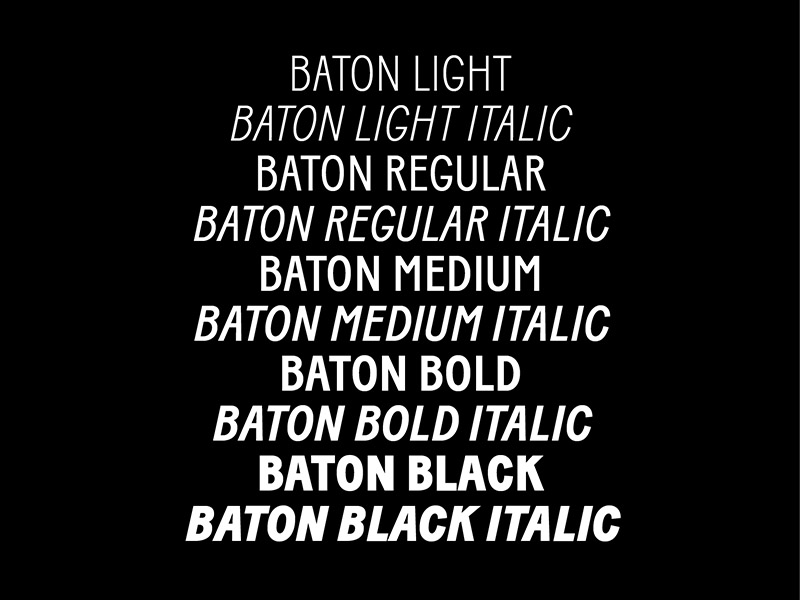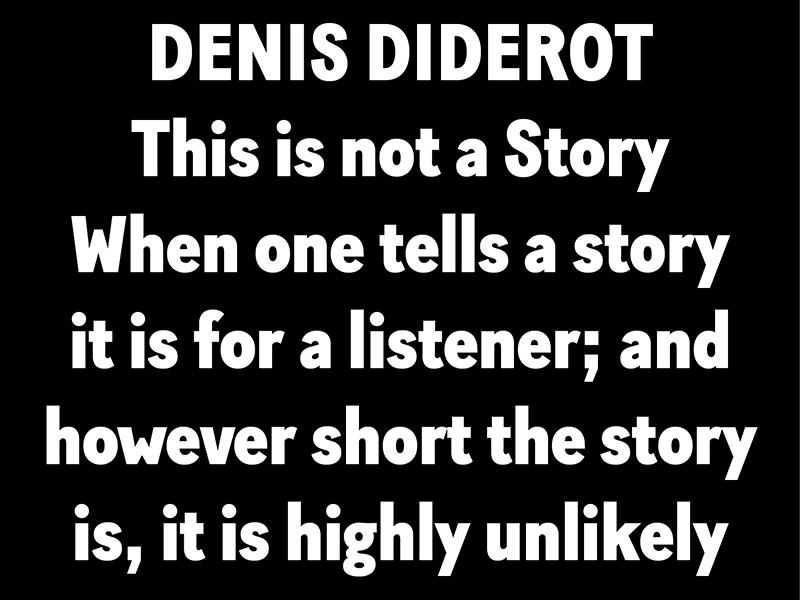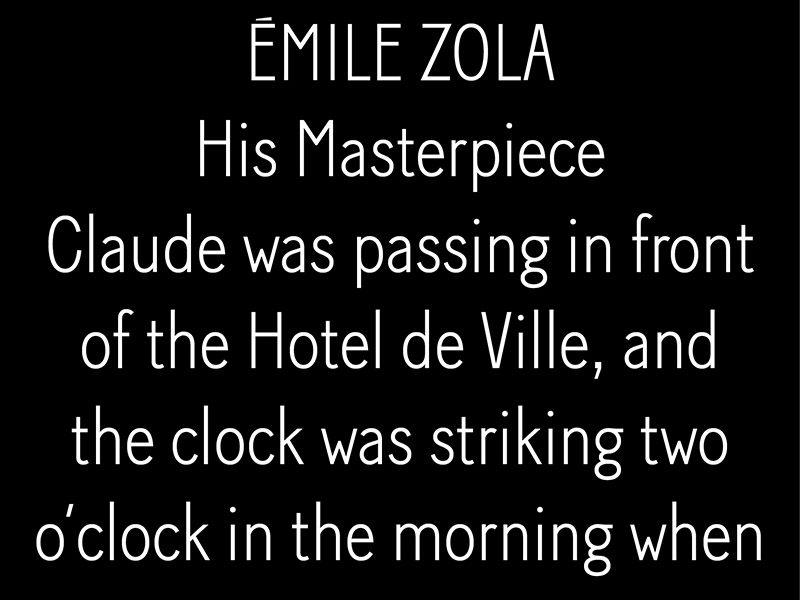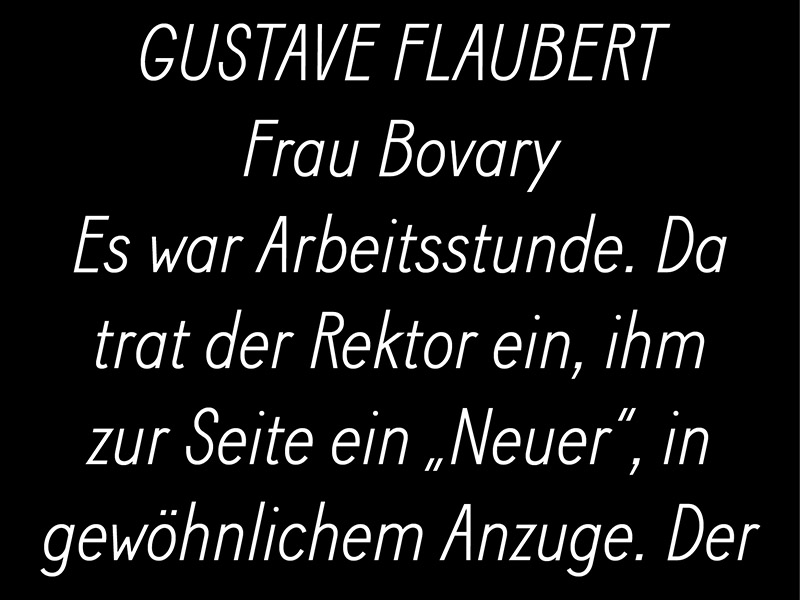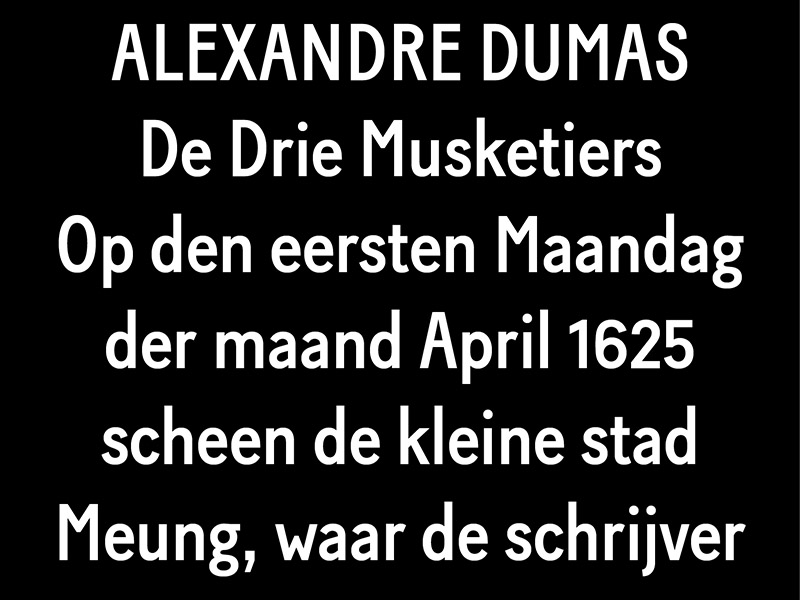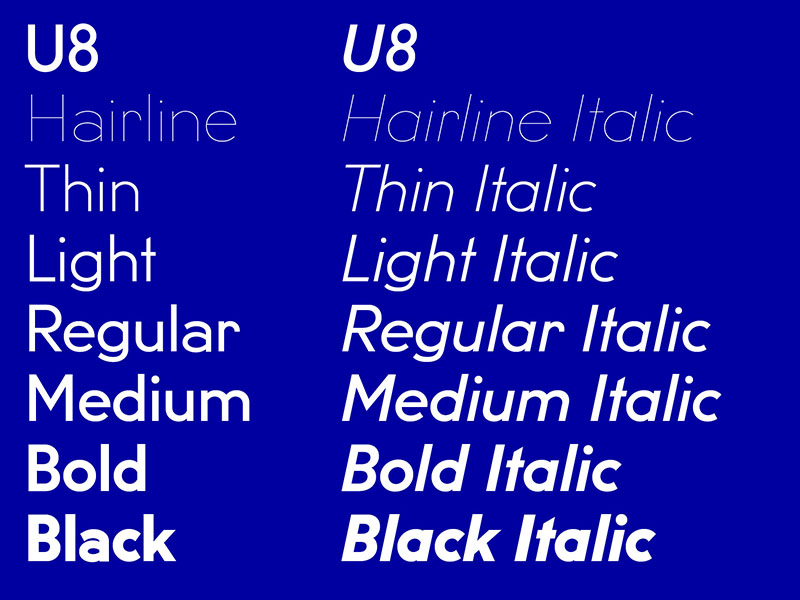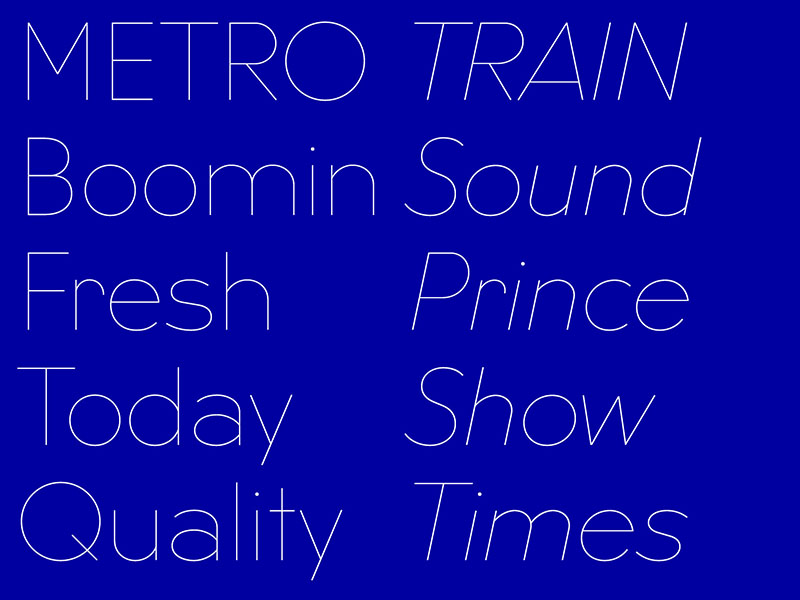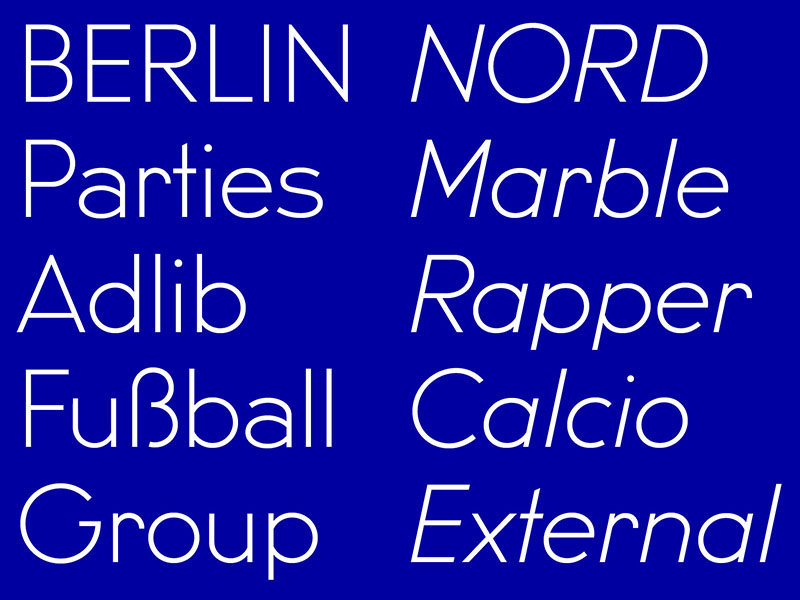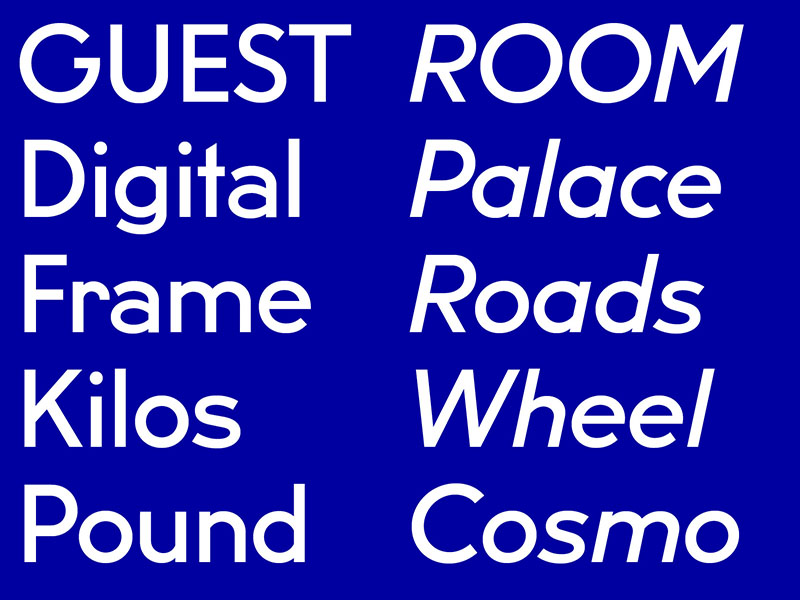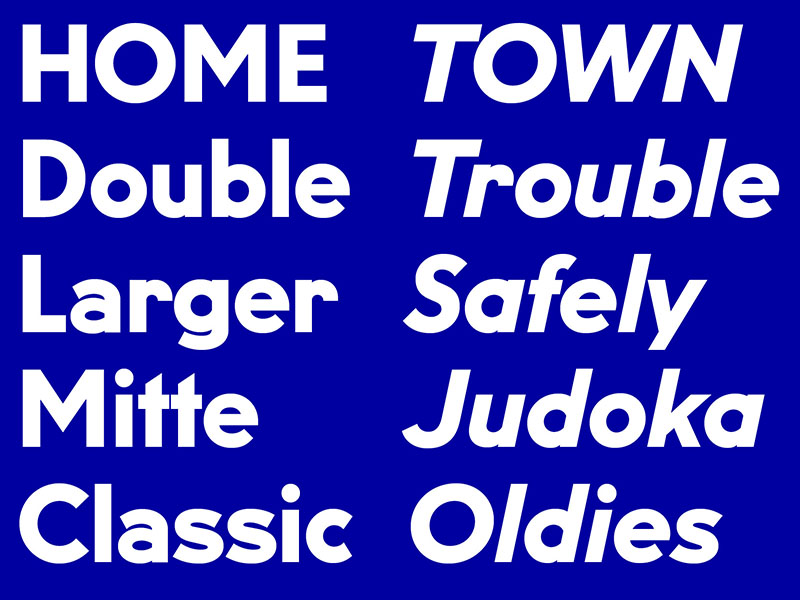
Baton und U8 (Fatype)
Vor kurz haben wir zwei neue Schriften rausgebracht:
Die Baton, was wir (Anton Koovit und Yassin Baggar) ursprünglich für das französische Magazin GQ gestaltet haben.
Die U8, was sich auf den Schilder der Berliner U-Bahn Linie 8 basiert. Nach viel Arbeit (2008 wurde das Projekt von Anton Koovit gestartet), kam die Schrift in Januar raus. Jetzt sind Italics schnitte auch dabei.